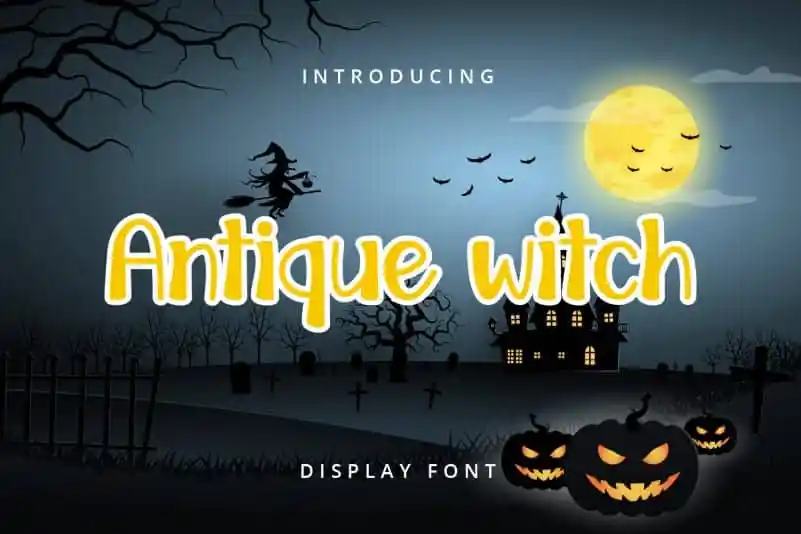
Antique witch Display Font – Download Grátis
A Fonte Antique Witch Display é uma escolha ideal para quem busca trazer um toque criativo e distintivo à sua estratégia de design durante a Halloween. Esta fonte estilizada, com suas cores assombrosas, é perfeita para aqueles que desejam destacar suas ideias em ambientes festivos ou criar designs memoráveis. Seja num calendário temático, etiquetas de presentes, selos, cartazes ou até mesmo em logotipos de empresas, a Antique Witch Display proporciona um visual marcante e único. Ideal para conjugar com outros estilos gráficos que evocam atmosferas misteriosas e fantásticas da época festiva, esta fonte permite transformar uma ideia já genial num projeto memorável. Combinada com cores sóbrias ou vibrantes, a Antique Witch Display é um verdadeiro destaque em qualquer página de apresentação, sejam elas para projetos profissionais ou simplesmente interesses pessoais.